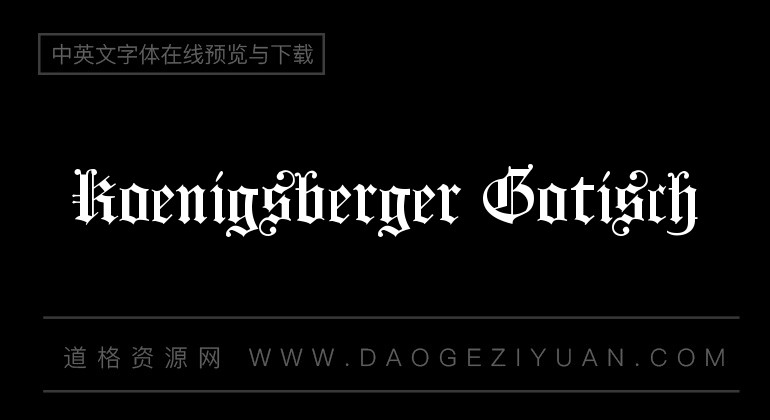
Koenigsberger Gotisch是一种黑体字体,最初由德国印刷业者Erhard Ratdolt在15世纪晚期于东普鲁士的科尼斯堡(今波兰城市卡利尼克)所创造。该字体经常被用于书籍、广告、招牌和海报等印刷品中,特别是在德国和欧洲地区。Koenigsberger Gotisch的特点是其粗细的笔画,以及其与古德意志体(Gothic) 相似的字形。它是一种古老而又有力的字体,经常被用于强调和突出效果。内容介绍
Koenigsberger Gotisch是一款非常不错的手写艺术字体,具有很好的视觉感,适合于文化类的宣传设计、商业类品牌的广告和产品包装设计以及个性化文字排版等较多场景。